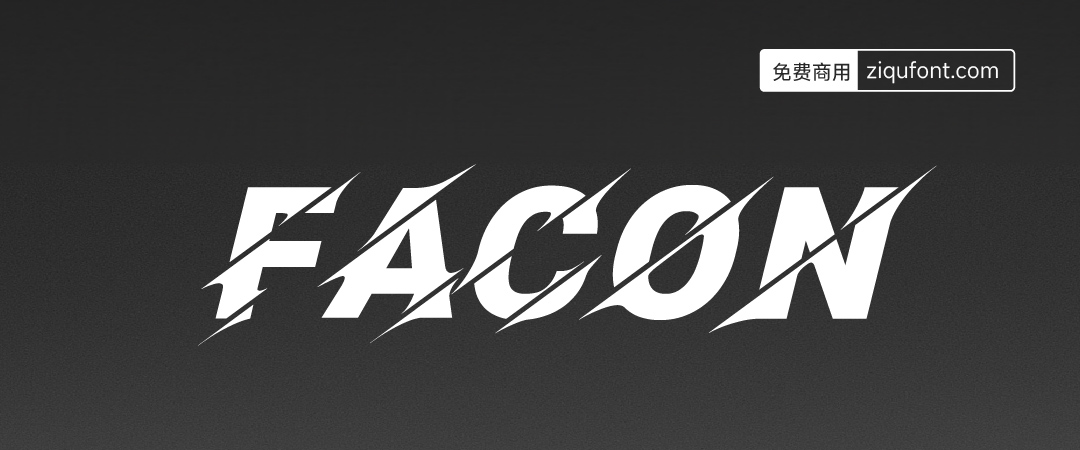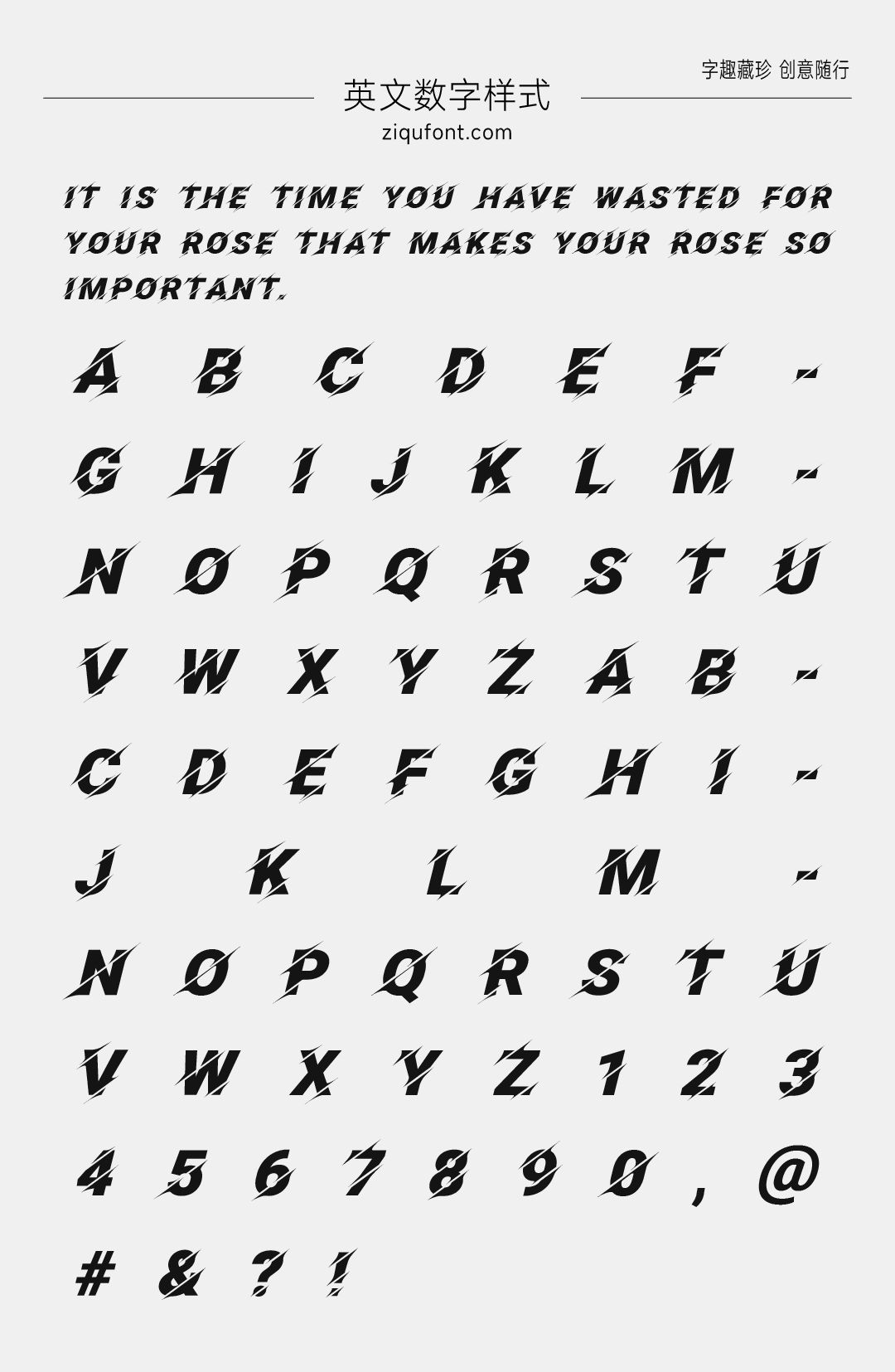
Facon
基本信息:Facon 字体由美国字体设计师 Alejo Bergmann 设计,于 2008 年 9 月 12 日创建。它是一款体育展示字体,包含 96 个字形,129 个字符。
设计特点:Facon 字体的名字来源于葡萄牙语 “fação”,意为 “大砍刀”,这很形象地描述了其设计特点。该字体具有棱角分明、锋利的形状,几乎就像刀刃一样。它采用几何形式,对比强烈,粗细分明,给人一种威严、有力的感觉。字体结构粗壮,x 高度较高,字腔宽阔,具有简洁明了的视觉效果。
字体样式:Facon 字体主要有 Bold Italic(粗斜体)样式,字重为粗,字宽为中等。
语言支持:Facon 字体包含完整的字符集,支持 200 多种语言,能够满足不同语言用户的需求。